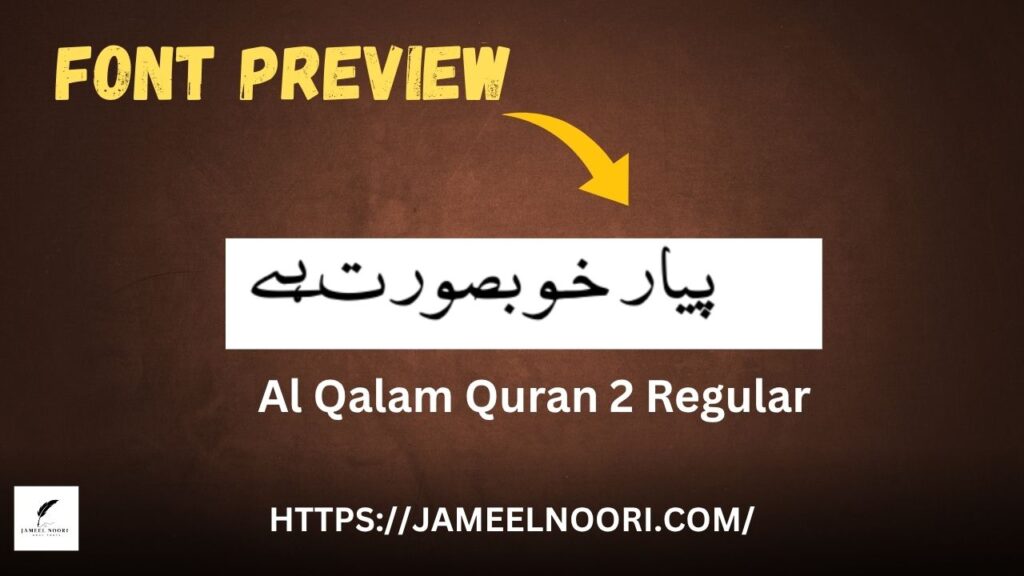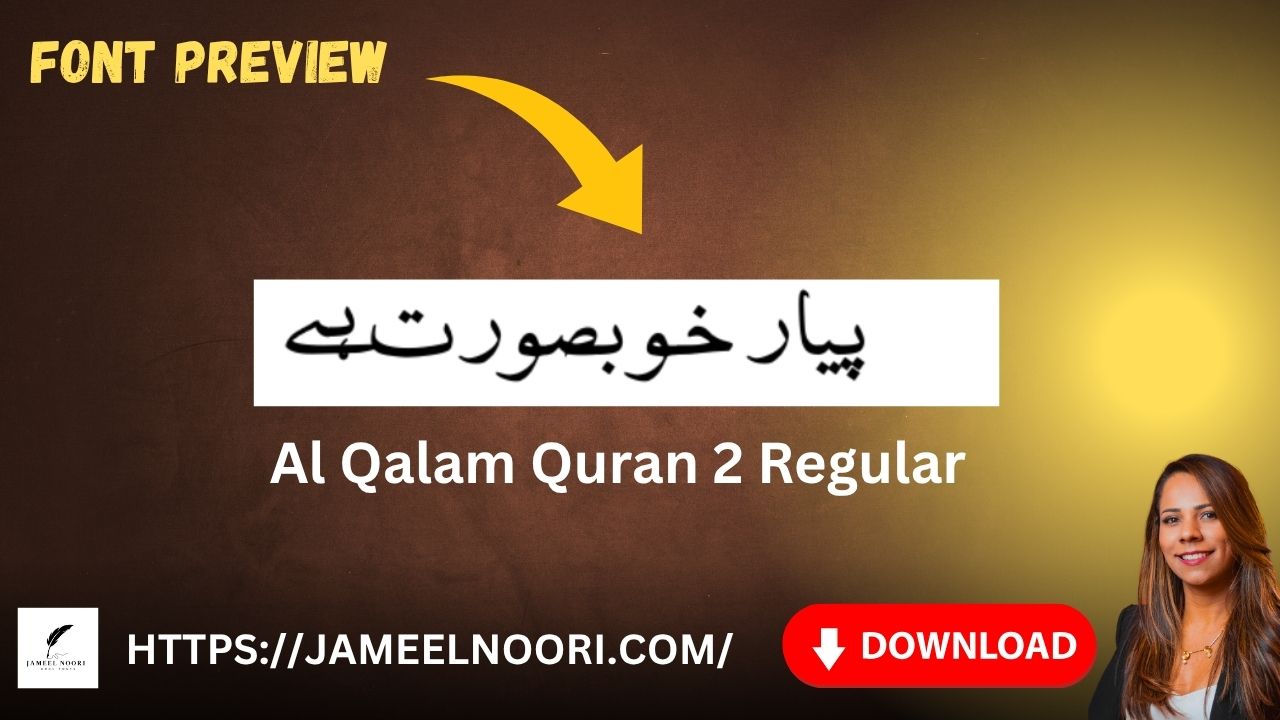
Introduction to Al Qalam Quran 2 Regular Font
Agar aap Quranic Urdu font dhoond rahe hain jo readability aur traditional script dono mein best ho, to urdu font Al Qalam Quran 2 Regular font aapke liye ek perfect choice hai. Ye font specially Quranic text aur Arabic-style Urdu writing ke liye design kiya gaya hai.
What Makes Al Qalam Quran 2 Regular Special?
- ✅ Quranic-style Nastaliq look
- ✅ Ideal for Naskh/Nastaliq lovers
Al Qalam Quran 2 Font Ka Istemaal Kahan Hota Hai?
Al Qalam Quran 2 Regular font ka istemaal kai jagah hota hai:
Pros and Cons of Al Qalam Quran 2 Regular
✅ Pros:
- Suitable for Islamic designs
- Clear and easy-to-read glyphs
❌ Cons:
- Limited glyph support (no stylistic variations)
- Not ideal for modern UI design
Expert Tip: Font ka behtareen istemaal kaise karein?
Agar aap ek reliable, clean aur visually balanced Urdu font dhoond rahe hain for Quranic and Islamic content, to Al Qalam Quran 2 Regular ek trusted choice hai. Iska low file size, classic look, aur compatibility isay Pakistani designers ke liye must-have font banata hai.